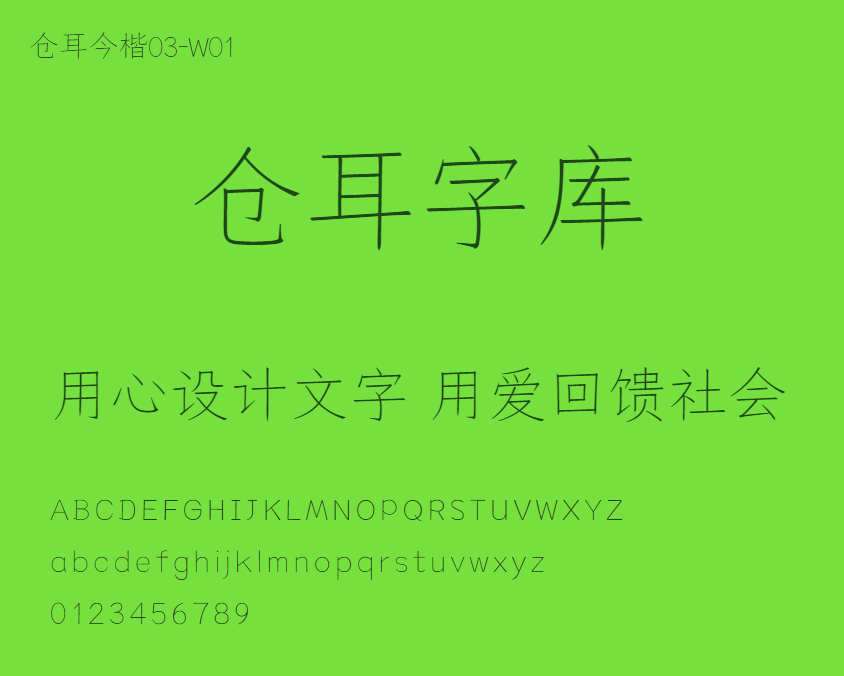
仓耳今楷03-W01
仓耳今楷03-W01,这款字体结构工整、笔画清晰,兼顾美观与易读性,适用于标题、正文、海报、包装、LOGO 等多种场景。字形优雅稳定,风格百搭耐看,适配日常排版与创意设计,让文字呈现更舒适、更具质感。仓耳今楷03-W01一笔一画,皆是细节,以均衡的比例、流畅的线条打造舒适视觉体验,字形端正大气,风格简约现代。无论是商业设计、品牌宣传还是日常排版,都能轻松驾驭,让文字更有格调与力量。仓耳今楷03-W01字体下载。